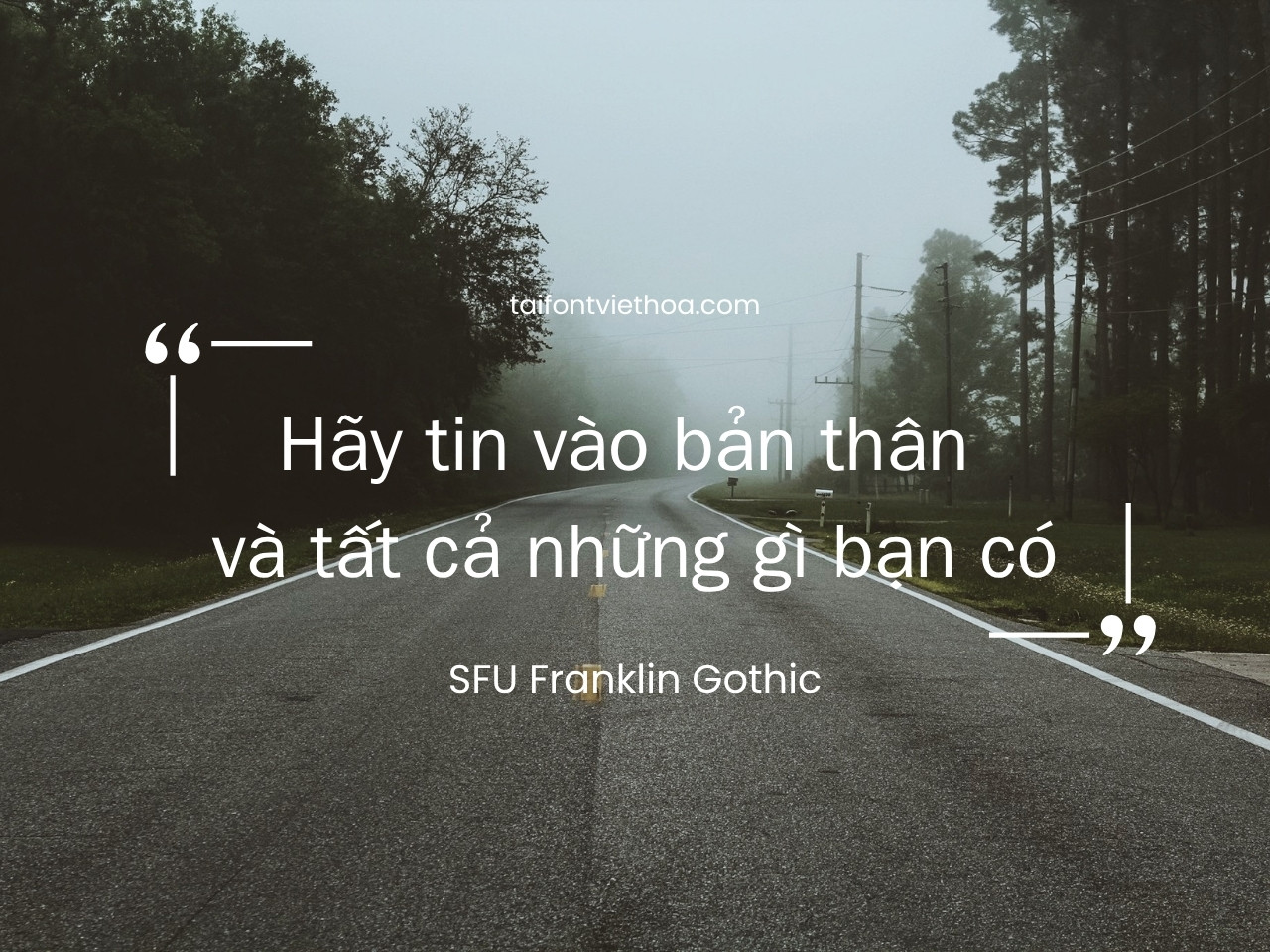
Font việt hóa SFU Franklingothic
Giới thiệu về font SFU Franklingothic – Di sản sans-serif mạnh mẽ của thiết kế Mỹ thế kỷ 20
SFU Franklingothic là phiên bản Việt hóa của kiểu chữ Franklin Gothic – một font sans-serif mang đậm phong cách công nghiệp Mỹ, được thiết kế lần đầu bởi Morris Fuller Benton vào năm 1902 cho American Type Founders. Với đường nét dày, chắc khỏe và tỷ lệ chữ cân đối, Franklin Gothic đã trở thành biểu tượng của truyền thông báo chí, quảng cáo và thiết kế hiện đại từ đầu thế kỷ 20 đến nay. Font này từng được dùng rộng rãi trong các tờ báo, poster tuyên truyền, bao bì sản phẩm và cả các chiến dịch branding toàn cầu.
Phiên bản SFU Franklingothic được Việt hóa công phu, đảm bảo hỗ trợ đầy đủ dấu tiếng Việt và các ký tự mở rộng. Taifontviethoa.comđã chọn lọc font này trong bộ sưu tập các sans-serif có tính ứng dụng cao và giá trị lịch sử lớn, nhằm mang đến giải pháp hoàn hảo cho những dự án đòi hỏi sự rõ ràng, tin cậy và chuyên nghiệp.
Thiết kế mạnh mẽ, dễ đọc và ứng dụng linh hoạt của SFU Franklingothic
SFU Franklingothic sở hữu hình dáng sans-serif truyền thống nhưng mang đặc trưng “mạnh – thẳng – rõ”. Đường nét chữ dày và đậm, giúp dễ đọc ở kích thước nhỏ hoặc trong môi trường hiển thị phức tạp. Kiểu chữ này thể hiện sự uy tín, đáng tin cậy nhưng vẫn đủ hiện đại để sử dụng trong nhiều ngữ cảnh.
Ứng dụng lý tưởng: thiết kế tiêu đề, tạp chí, biển hiệu, bao bì sản phẩm, hệ thống nhận diện thương hiệu, giao diện web và các chiến dịch marketing quy mô lớn. Ngành nghề phù hợp: truyền thông, báo chí, bất động sản, công nghiệp, tài chính, công nghệ và các lĩnh vực cần truyền tải thông điệp rõ ràng, có trọng lượng và dễ ghi nhớ.